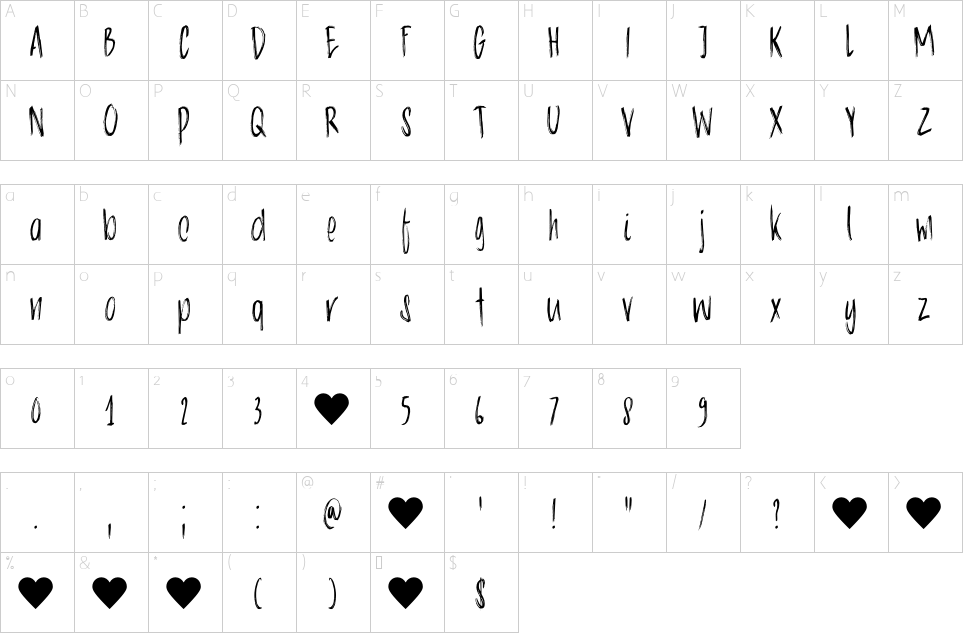
A DK Chocolatte é uma fonte que traz aos seus projetos um toque suave e quente do doce chocolate. Desenhada por Hanoded, esta fonte foi criada para quem aprecia a beleza minimalista misturada com um toque delicado de elegância. Com seu design cuidadosamente pensado, DK Chocolatte é perfeita para gráficos e designers que desejam dar um toque suave aos seus materiais digitais. A fonte é versátil e pode ser usada em diversos tipos de projetos, desde identidades visuais até aplicativos móveis. Com uma aparência natural e agradável, ela é ideal para quem busca uma alternativa não apenas agradável ao público visual que adora chocolate. Recentemente, mais de 13.600 pessoas já experimentaram o rico sabor desta fonte. Se você está procurando por algo que vai deixar seu design mais sofisticado e elegante, sem dúvida a DK Chocolatte é uma escolha ótima para você. Não se esqueça de explorar os diferentes graus de negrito para adaptá-la ao seu projeto específico. Descubra o doce lado desta fonte em seus projetos digitais hoje!